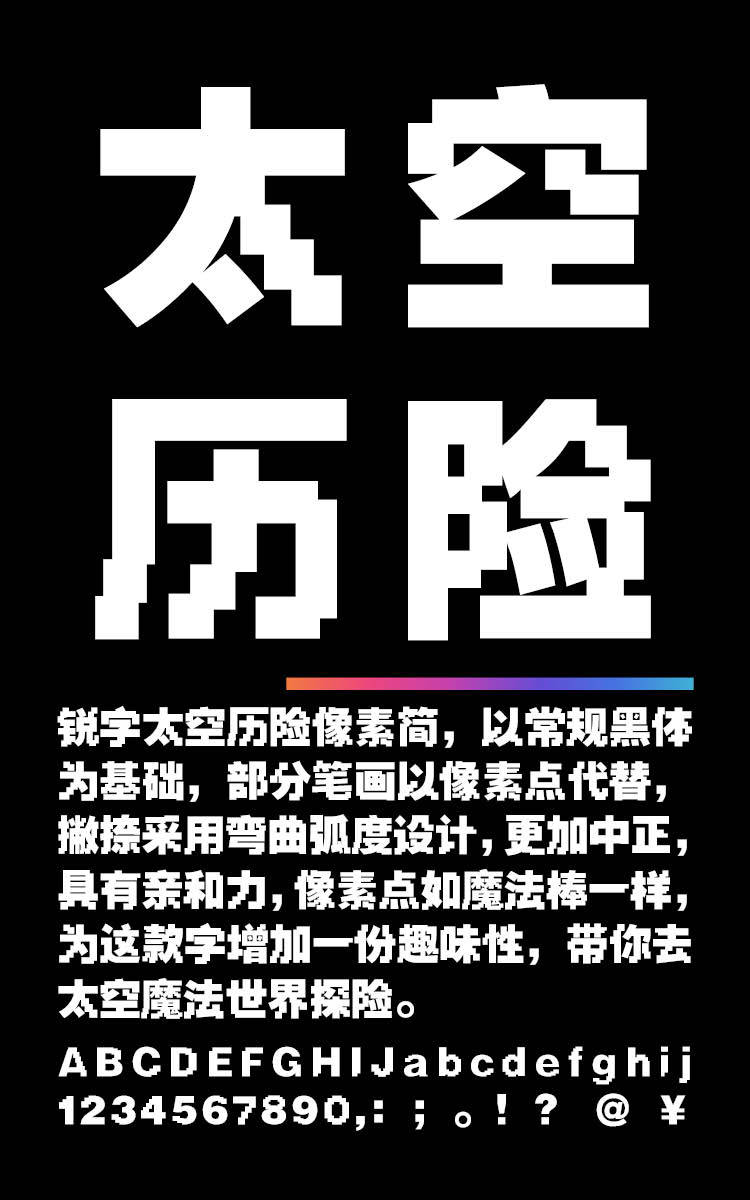
锐字太空历险像素简
锐字太空历险像素简,这款字体结构工整、笔画清晰,兼顾美观与易读性,适用于标题、正文、海报、包装、LOGO 等多种场景。字形优雅稳定,风格百搭耐看,适配日常排版与创意设计,让文字呈现更舒适、更具质感。锐字太空历险像素简一笔一画,皆是细节,以均衡的比例、流畅的线条打造舒适视觉体验,字形端正大气,风格简约现代。无论是商业设计、品牌宣传还是日常排版,都能轻松驾驭,让文字更有格调与力量。锐字太空历险像素简字体下载。
字体认特征:部分笔画利用小方块像素点组成,字体笔画较粗。规范、工整,容易辨认,适用于LED屏等电子屏幕,体现科技感和现代感。适用于游戏、海报等场景。